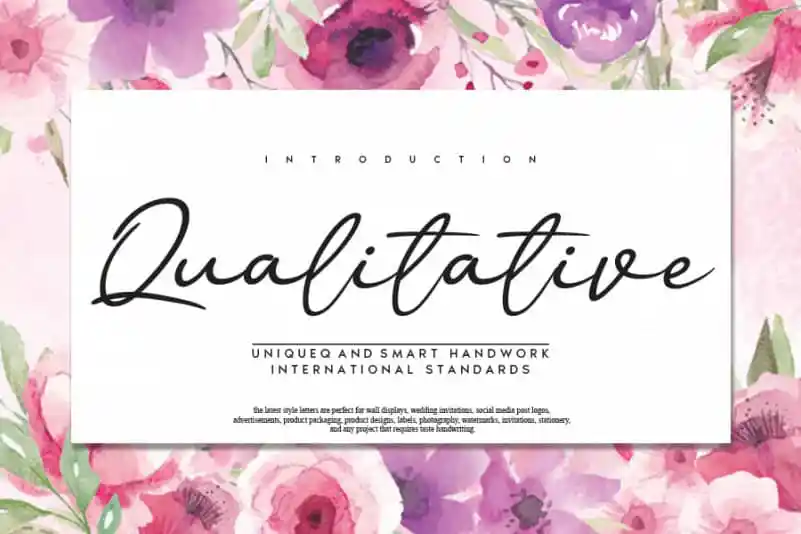
Qualitative Handwritten Font
A Qualitative Handwritten Font é uma fonte manuscrita fluida que se destaca por sua elegância e estilo inconfundível. Perfeita para projetos pessoais ou profissionais, essa fonte é especialmente indicada para aqueles que valorizam design único e autêntico. Ela pode transformar seus trabalhos em algo ainda mais memorável, criando designs impactantes e singulares sem sair da sua identidade única. Se apaixone pelo seu estilo distintivo e eterno, ele é perfeito para quem busca originalidade na linguagem visual. Esta fonte será um acréscimo inigualável a qualquer projeto que você estiver criando.